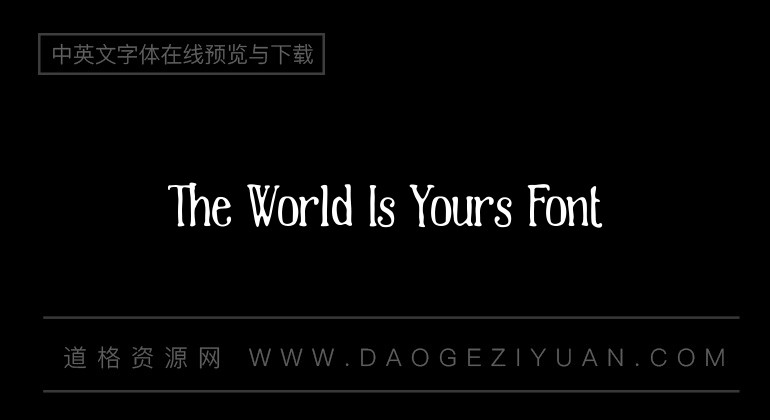
The World Is Yours Font
The World Is Yours Font 是一种免费的手写风格的字体,它于2019年由设计师Jeremiah Shoaf创作并发布。这种字体采用了不规则的线条和圆润的笔画,给人一种随性而自然的感觉,特别适合用于标题、标志和海报等设计作品中。 The World Is Yours Font 包括大写字母、小写字母、数字和一些常见的标点符号,它的设计灵感来源于20世纪早期的手写信件和招贴画。这种字体的特点是字母之间的间距比较紧凑,适合用于需要强调紧凑感的设计风格中。 总的来说,The World Is Yours Font 是一种非常有特点和创意的字体,可以为设计师提供一个独特而具有表现力的选项。
The World Is Yours Font是一款非常不错的手写艺术字体,具有很好的视觉感,适合于文化类的宣传设计、商业类品牌的广告和产品包装设计以及个性化文字排版等较多场景。